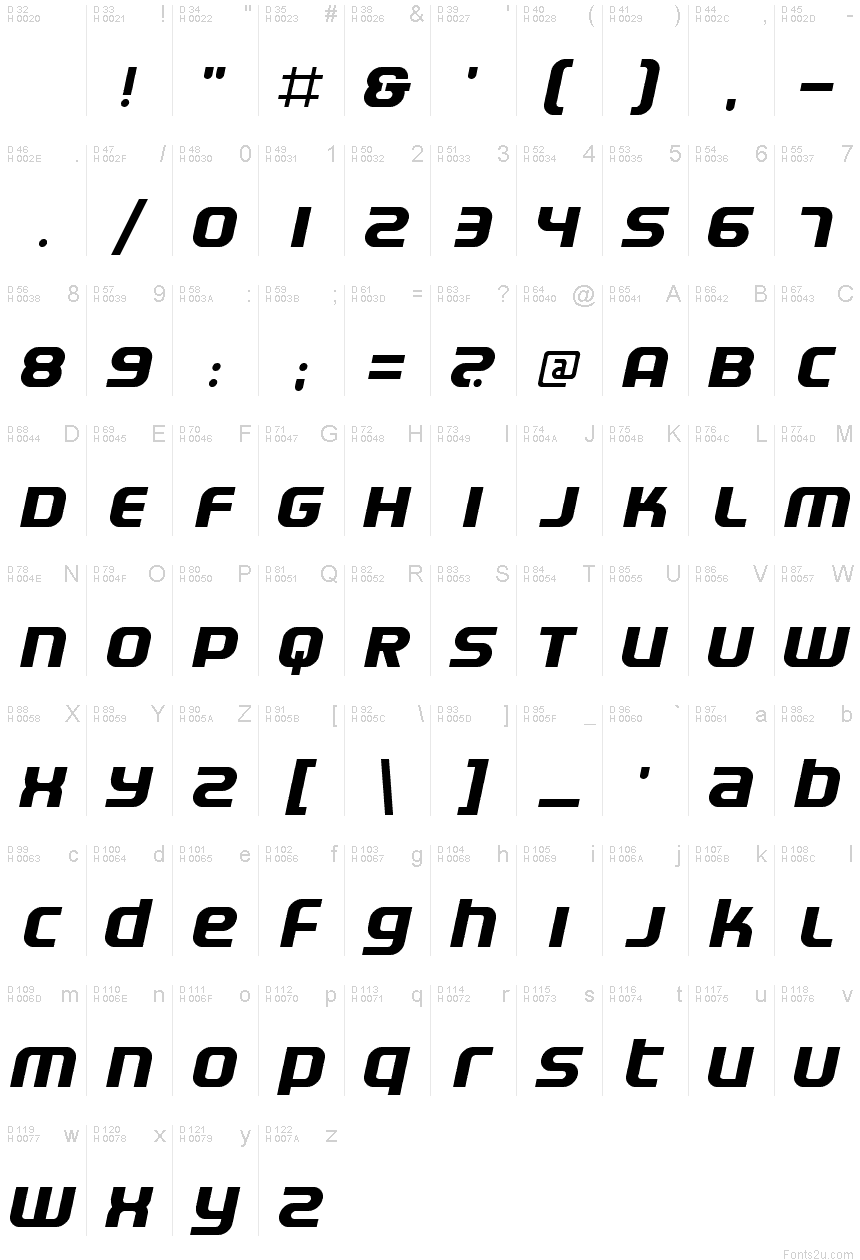
Electrofied Italic
Electrofied Italic od dustBUST Fonts to nowoczesny, darmowy krój pisma typu display. Jako część rodziny Electrofied, stawia na dynamikę: ostro nachylone litery, masywne krzywizny i kwadratowe wnęki tworzą wrażenie ciągłego ruchu, przypominając neonowy napis w pełnym sprincie. Kreski są gęste i wyraziste, co nadaje nagłówkom mocny, zwarty charakter, który czyta się szybko i zdecydowanie, bez wrażenia chaosu.
Electrofied Italic pozwala natychmiast nadać dynamiki brandingowi e-sportowemu, plakatom wyścigowym, tytułom sci-fi, grafikom technologicznym, nakładkom na streamy czy odważnym opakowaniom produktów. Ten darmowy font najlepiej sprawdza się w dużych rozmiarach, gdzie jego kanciaste krzywizny i rytmiczność naprawdę przyciągają wzrok. W tekście głównym połącz go z prostym, dyskretnym krojem bezszeryfowym, aby zapewnić energetycznym nagłówkom solidne, czytelne tło.